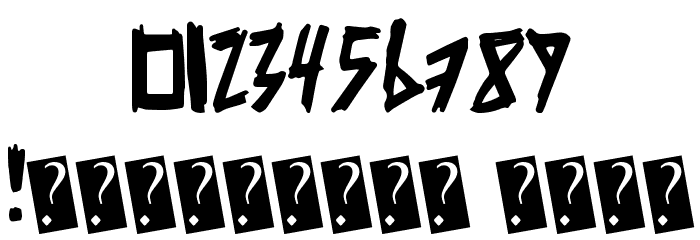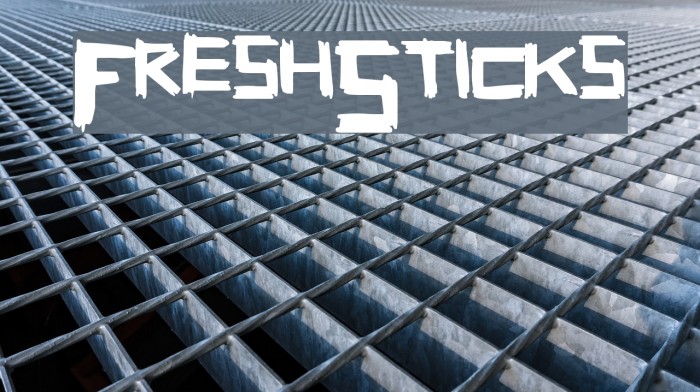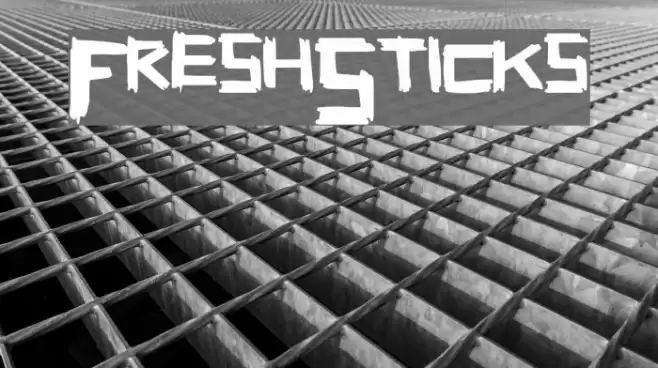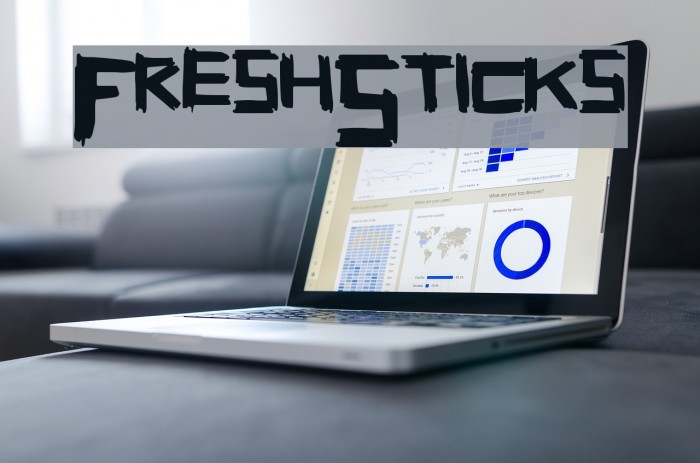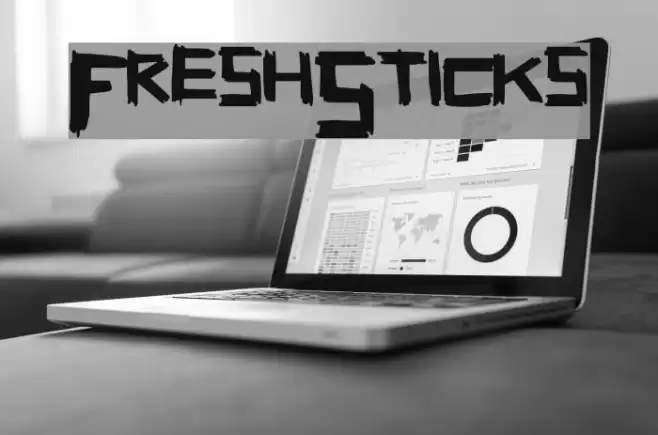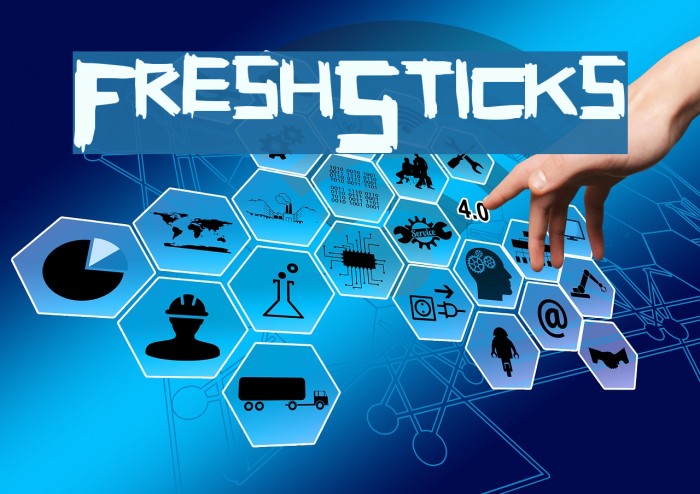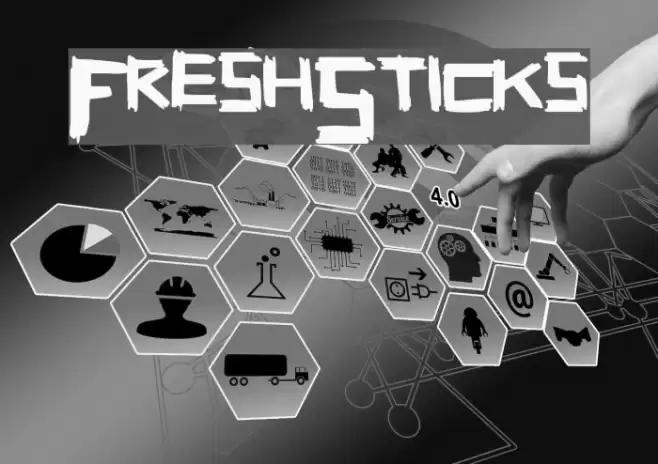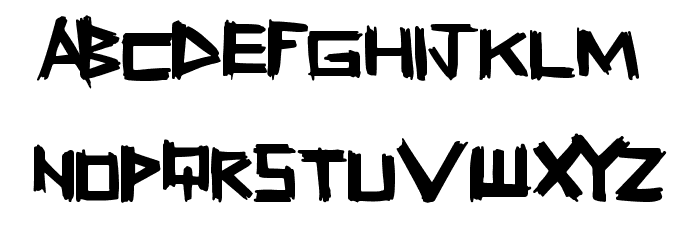
FreshSticks Font
| Nom | FreshSticks |
| Catégories | Cartoon |
| Style général | Modern, Urban, Edgy |
| Projets proposés | Ideal for streetwear branding, music album covers, urban-themed posters, and edgy graphic designs. |